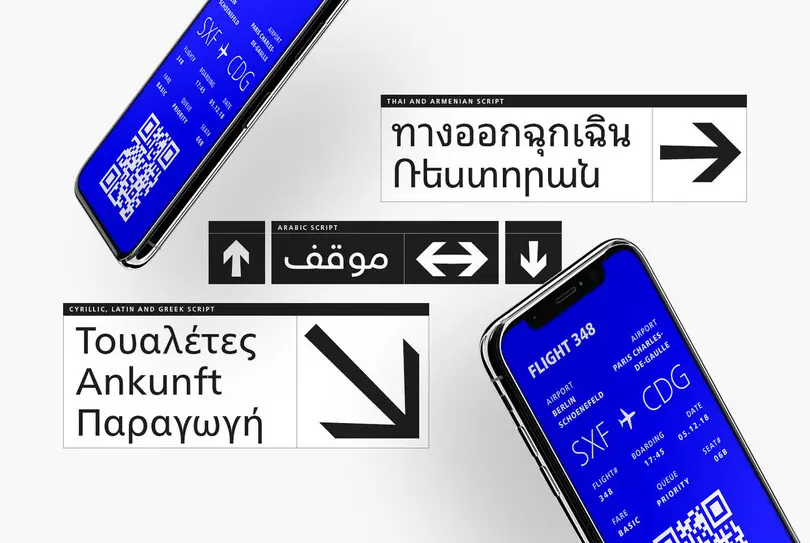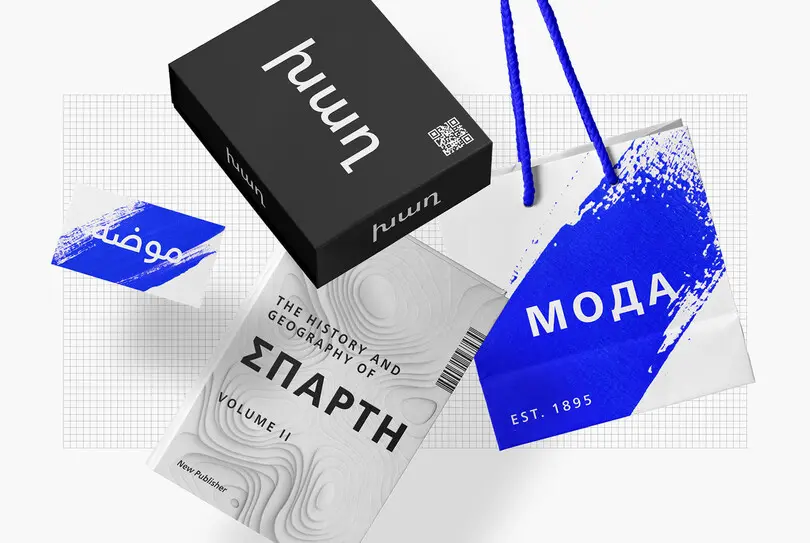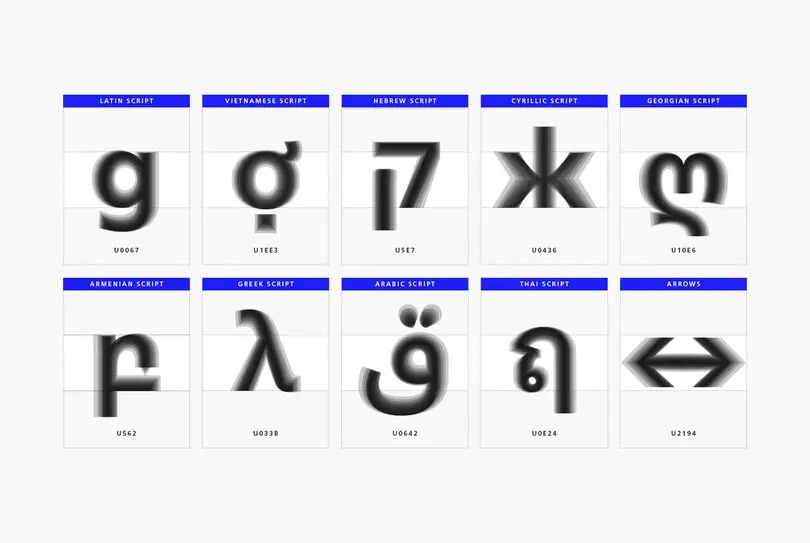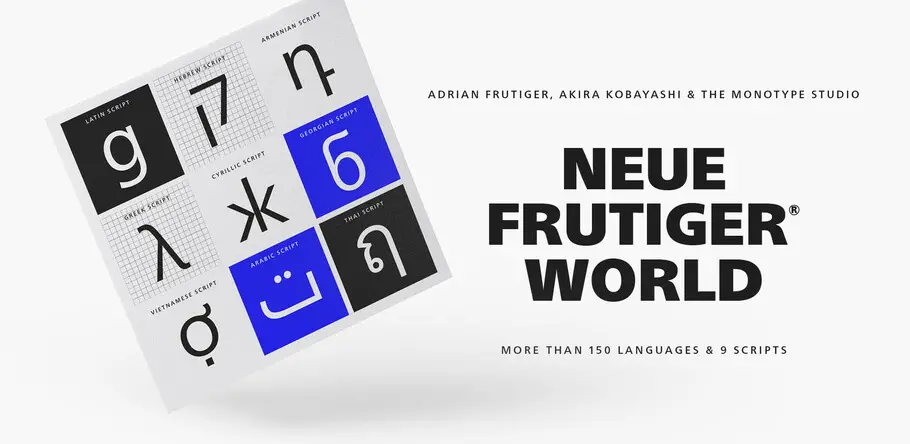
介绍一款真正的全球化字体:Neue Frutiger World
随着企业的全球化发展,品牌需要通过各种不同的语言和传播方式来保持其精心打造的视觉识别以及品牌格调。Neue Frutiger World——大型字体设计师团队磨砺多年的成果——能帮助应对这种日益增长的需求。
Neue Frutiger World延续了Adrian Frutiger设计的同名字体Frutiger,这套字体是他在70年代中期为巴黎附近的戴高乐机场设计的。易读性和可识别性在整套字体中贯穿始终,Monotype的字体设计总监小林章先生将其描述为具有 “某种有机的且友好的意味”。
Neue Frutiger World 可广泛用于从打印到屏幕的各种媒介
Neue Frutiger World保持着原有设计风格(design DNA),只是为了满足多语言需求对原有设计进行了扩展。Neue Frutiger World支持超过150种语言,包括希腊语、西里尔语、格鲁吉亚语、亚美尼亚语、希伯来语、阿拉伯语、泰语和越南语。
尽管Neue Frutiger World涵盖了如此广泛的语言,但整体设计依然保持着一致性。它在允许各种语言混排的同时,也能确保跨国公司对其品牌的一致性充满信心,无论是哪种语言。此款字体家族还能完美匹配Monotype新的CJK字体设计:翔鹤黑体、Tazugane Info以及Seol Sans。这特别重要,因为对于许多公司而言,通过定制字体来涵盖所有这些语言在成本和时间上都是不切实际的
Neue Frutiger World凭借10种字重为品牌提供广泛的语言支持
“在中国、日本和韩国,一款具有人文主义风格的新字体有很大的市场需求,” Monotype字体设计总监、Neue Frutiger World设计团队的负责人小林章先生说。“我们相信,我们可以用一种新颖的方式来满足这一需求。”
Neue Frutiger World 为所有的品牌接触点提供一致的排印效果
“在Neue Frutiger World以及与之匹配的CJK字体出现之前,西方品牌很难找到一个包含中文、日文及韩文并能与拉丁文相匹配的字体家庭。” 小林章先生补充说,“他们可能会找一款相似的字体,但不能保证CJK家族中的粗体是否能与他们拉丁文中的粗体相匹配。Neue Frutiger World提供了一种更好的解决方案。”